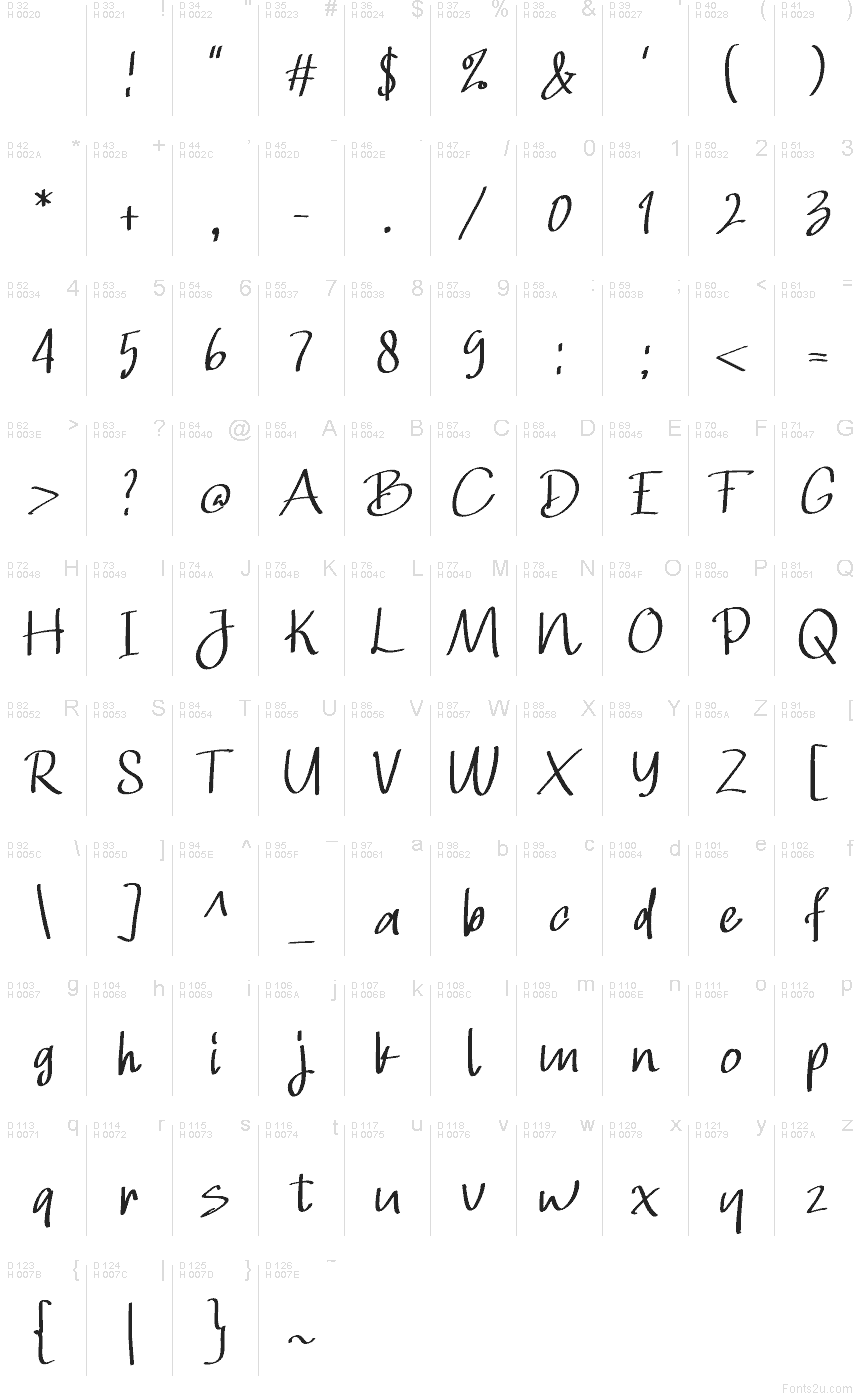
Gregory Hwang
Шрифт Gregory Hwang від Hello Good Studio — це безкоштовна рукописна гарнітура з плавним скриптовим стилем і легким, «пензликовим» ритмом. Літери поєднуються довгими штрихами та м'якими, ледь нерівними вигинами, що надає дизайну швидкого, персонального вигляду, не втрачаючи акуратності.
Gregory Hwang чудово підходить для логотипів, запрошень, графіки з цитатами, упаковки товарів, постів у соцмережах та брендингу в стилі автографа, оскільки його зв'язні форми передають ефект мальованої лінії в коротких фразах. Цей безкоштовний шрифт також стане в пригоді для вітальних листівок, меню кав'ярень, назв подій та декоративних етикеток, коли вам потрібен невимушений і виразний стиль.